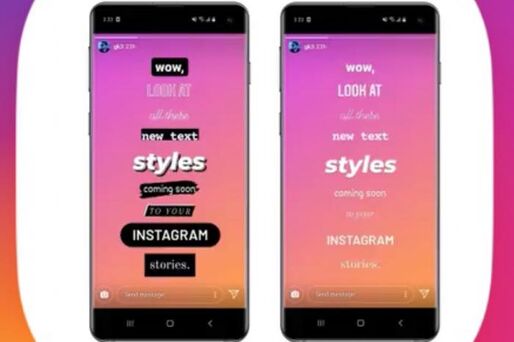
インスタグラムのストーリーには欠かせない「フォント」。ストーリーの写真や動画に文字入力できる機能として重宝している人も多いでしょう。これまでのフォント5種類に、新しく4種類の字体が追加されました。
明朝体が利用可能に?(2020年5月8日追記)
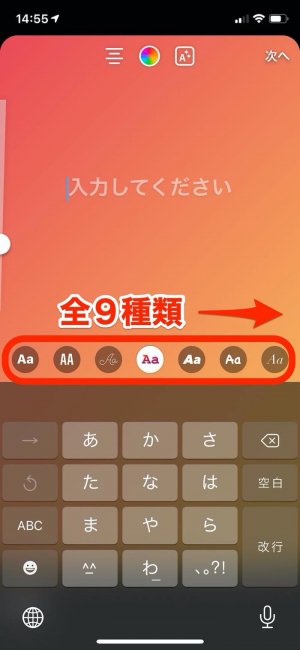
ストーリー編集画面で文字入力ボタン([Aa])をタップすると、画面中央にフォントメニューが表示されます。左方向へスワイプすると、全フォントが確認できます。
加工や工夫ひとつで多彩な楽しみ方ができるストーリーにオシャレでデザイン性のあるフォントが加わり、さらに自分らしいストーリー投稿が作れるでしょう。